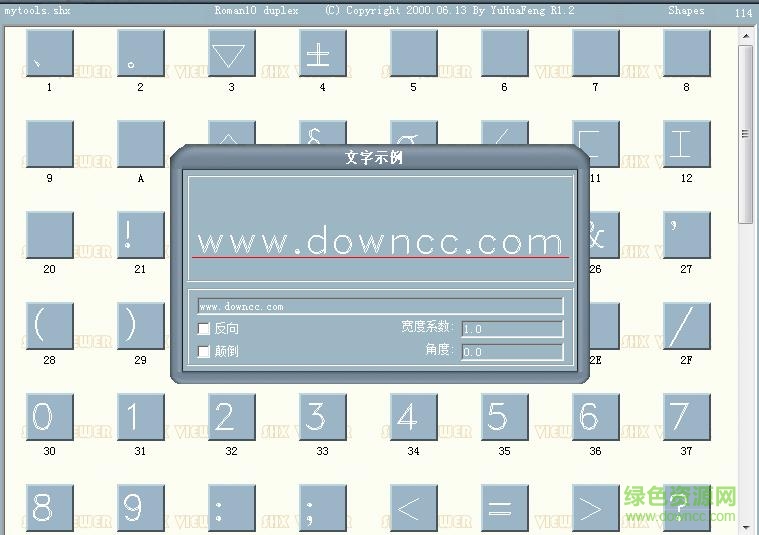
mytools.shx字體的使用用途十分廣泛,在cad的圖紙制作以及各類設(shè)計過程中都需要使用到,同時在眾多圖紙的打開過程中也需要此字體文件來顯示出其內(nèi)的各類符號以及字體!
mytools.shx在使用的時候?qū)⒆屇愀惺艿讲诲e的字形顯示效果,擁有多重字體紋理,能夠顯示出不錯的圖紙信息,帶給你優(yōu)質(zhì)的使用體驗!
2、如字母l,就跟數(shù)字的1字沒有區(qū)別,常用的i,j,k等,也離手寫的形態(tài)差別太遠。對此,mytools.shx都進行了重新繪制,使之看起來更為親切和清晰。